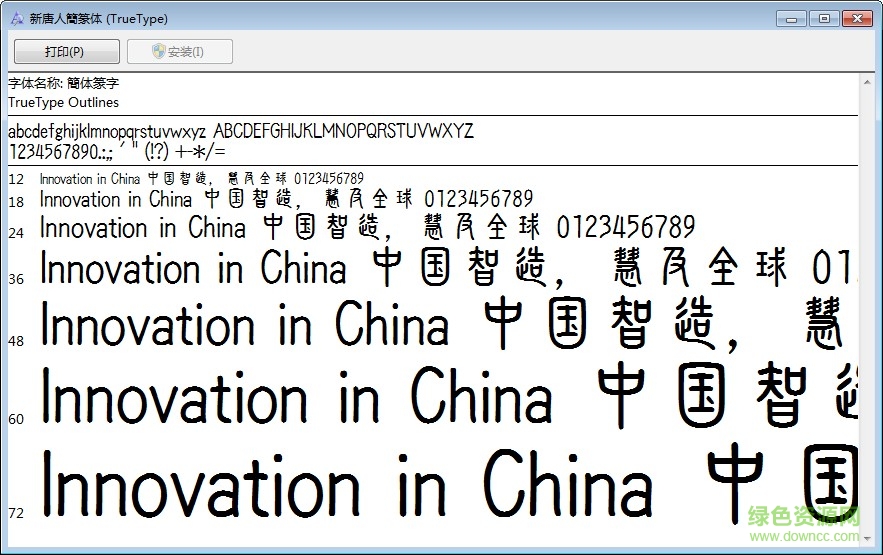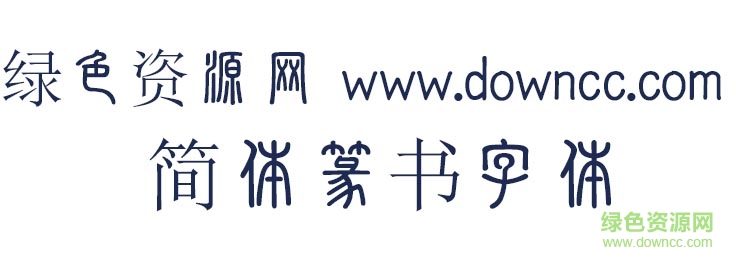
簡體篆書字體
簡體篆書字體是一款經(jīng)典的簡體篆書字體,字形精美文雅,線條簡練生動,可應(yīng)用于廣告設(shè)計、藝術(shù)設(shè)計等領(lǐng)域,喜歡的朋友歡迎在綠色資源網(wǎng)下載!
簡體篆體簡介:
簡體篆書字體是一款應(yīng)用于設(shè)計方面的簡體篆體字體,字形曲線柔美,非常適合用于各類設(shè)計當(dāng)中,讓你的主題更鮮明,效果更為明顯。有需要的朋友趕快來綠色資源網(wǎng)下載使用吧!